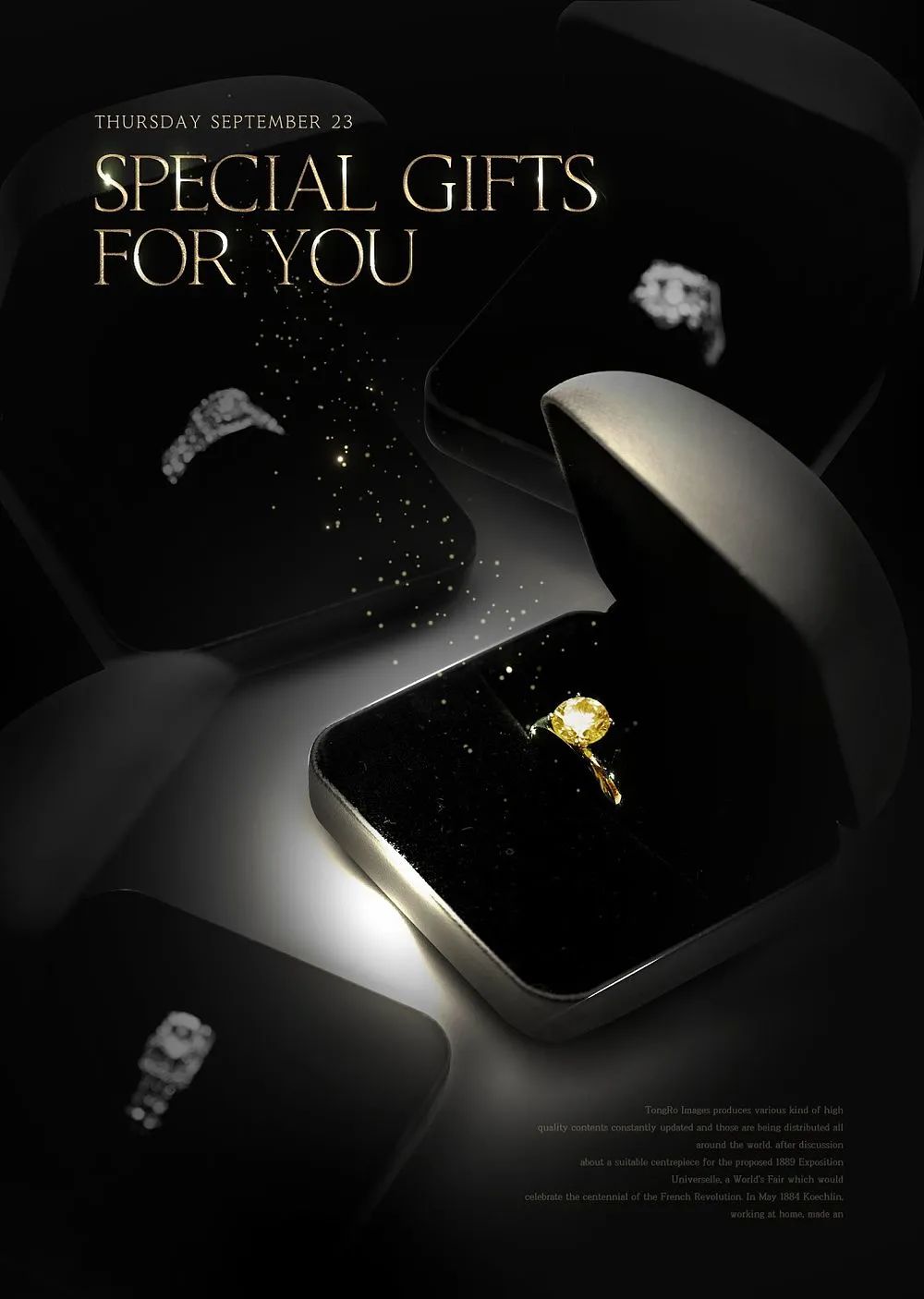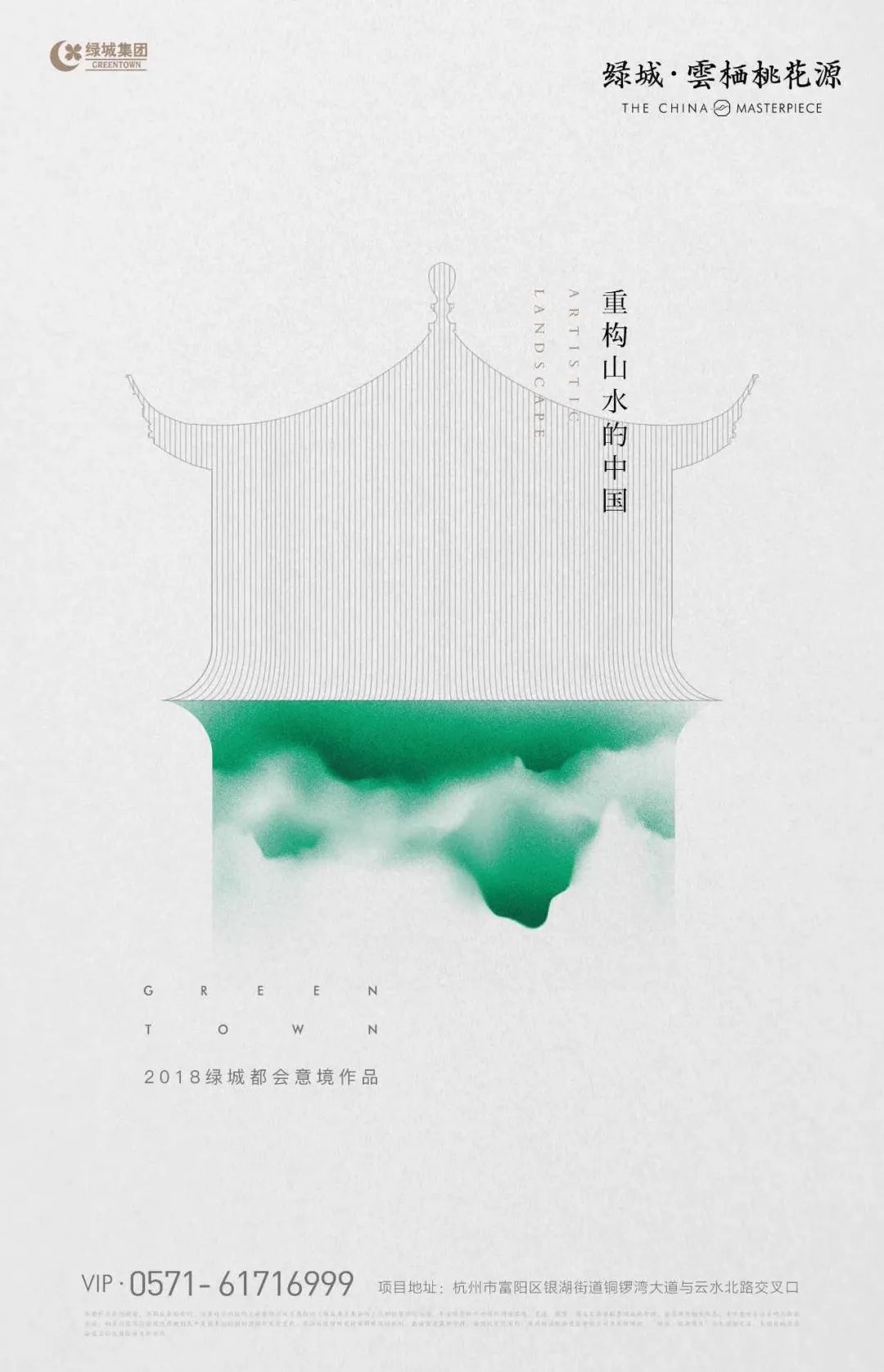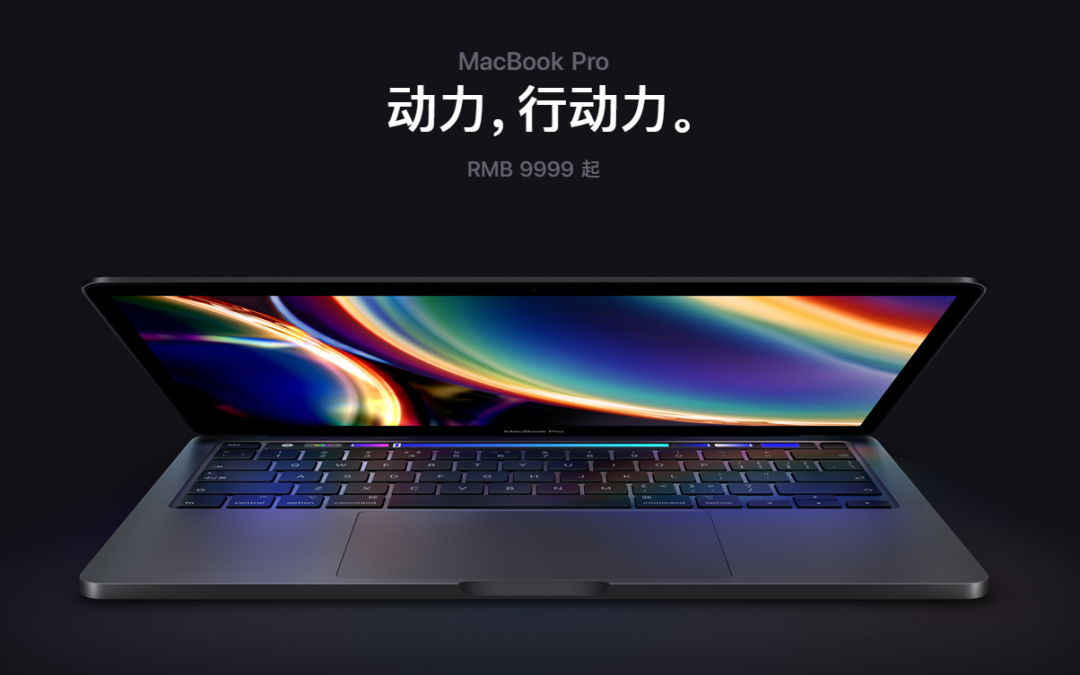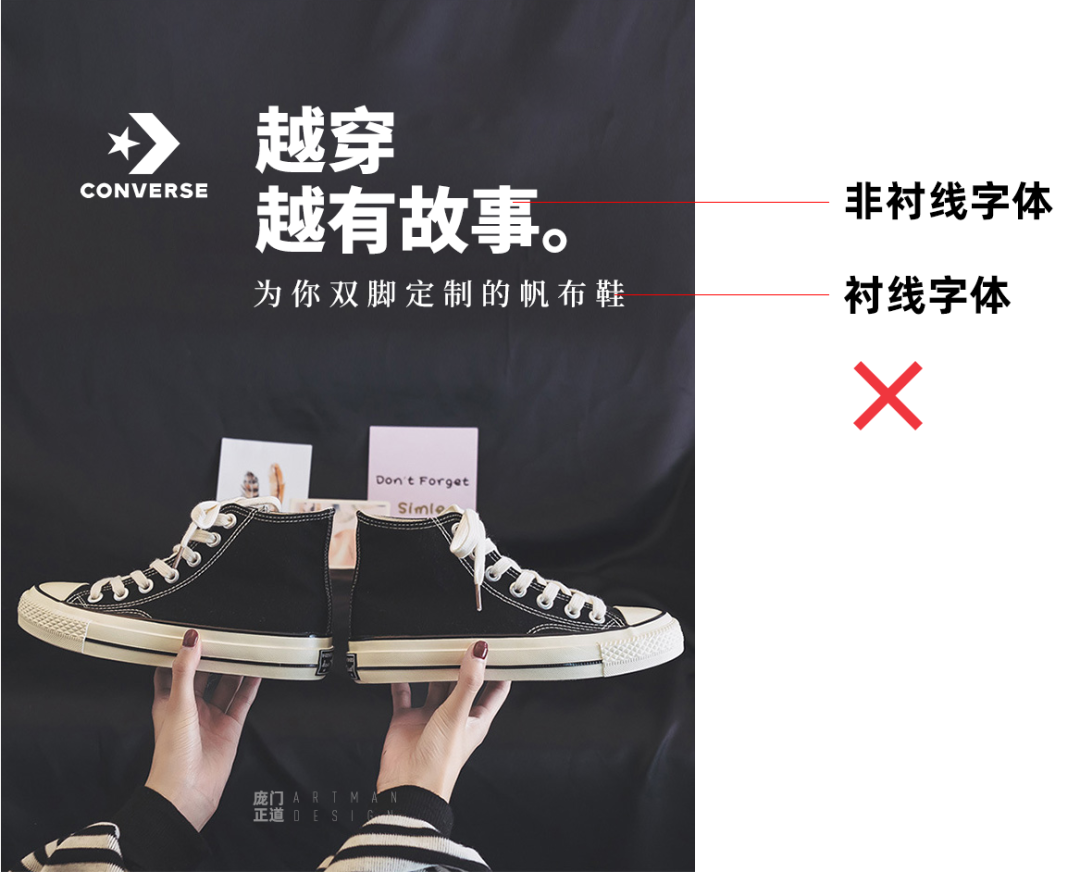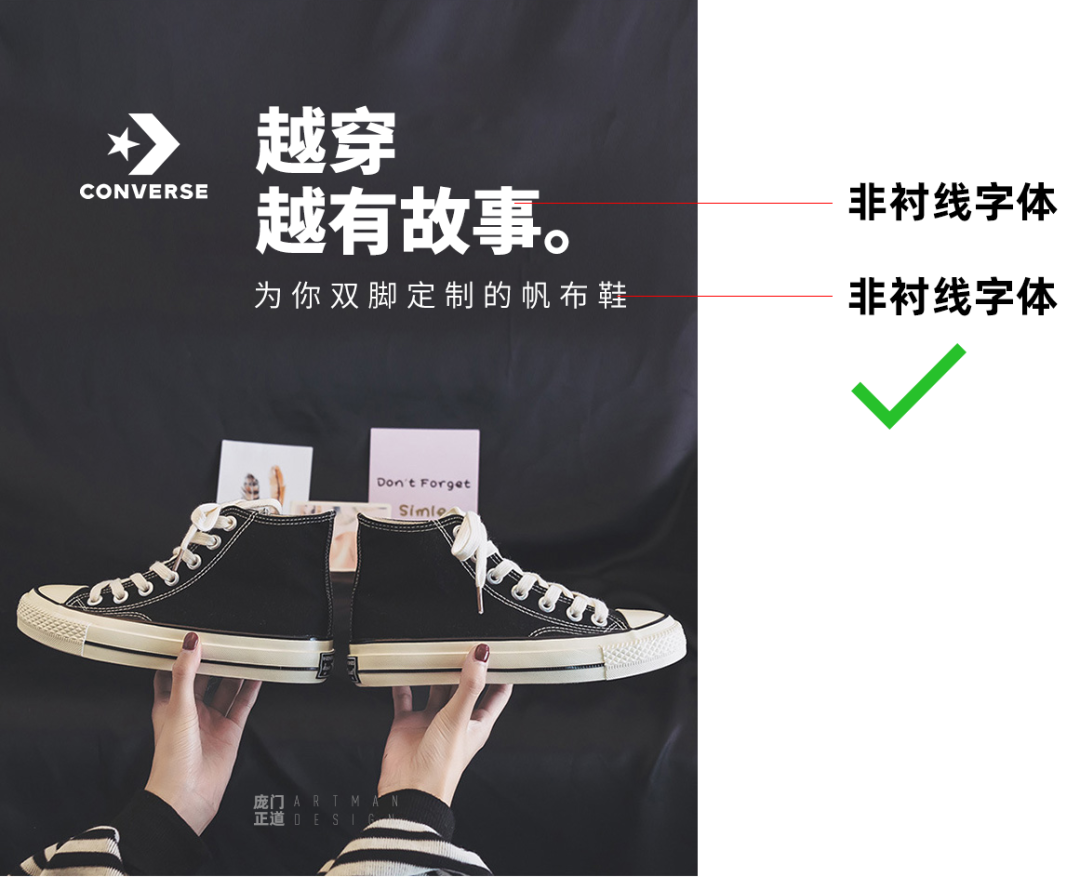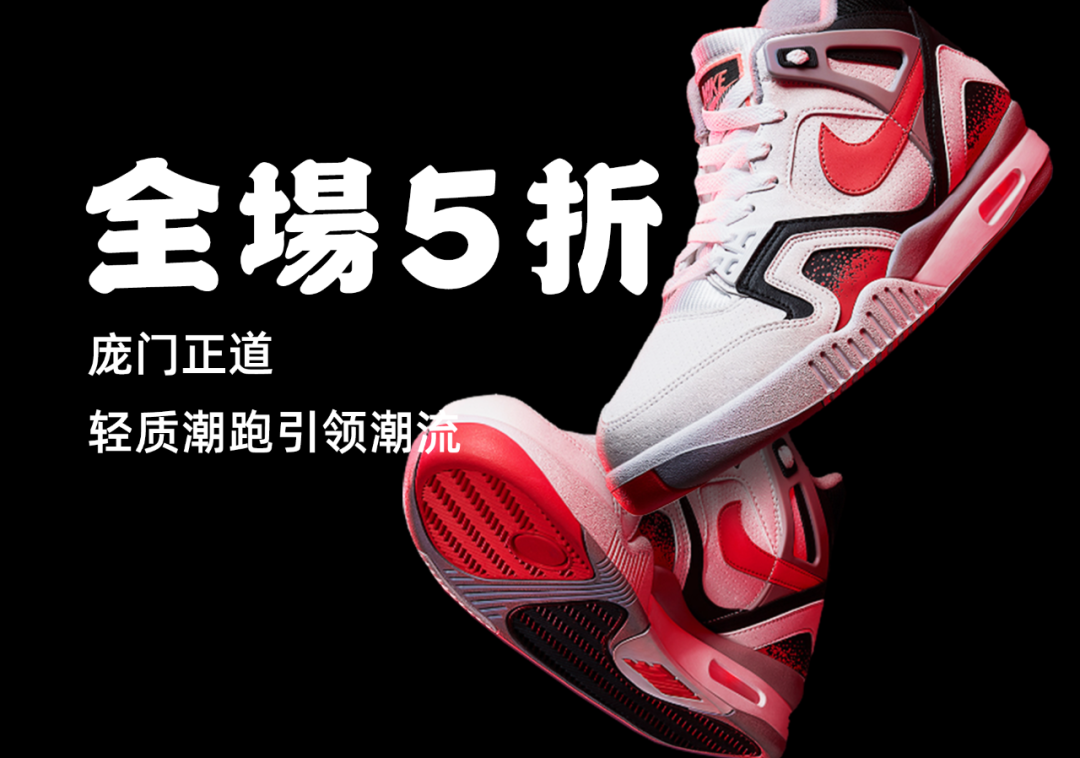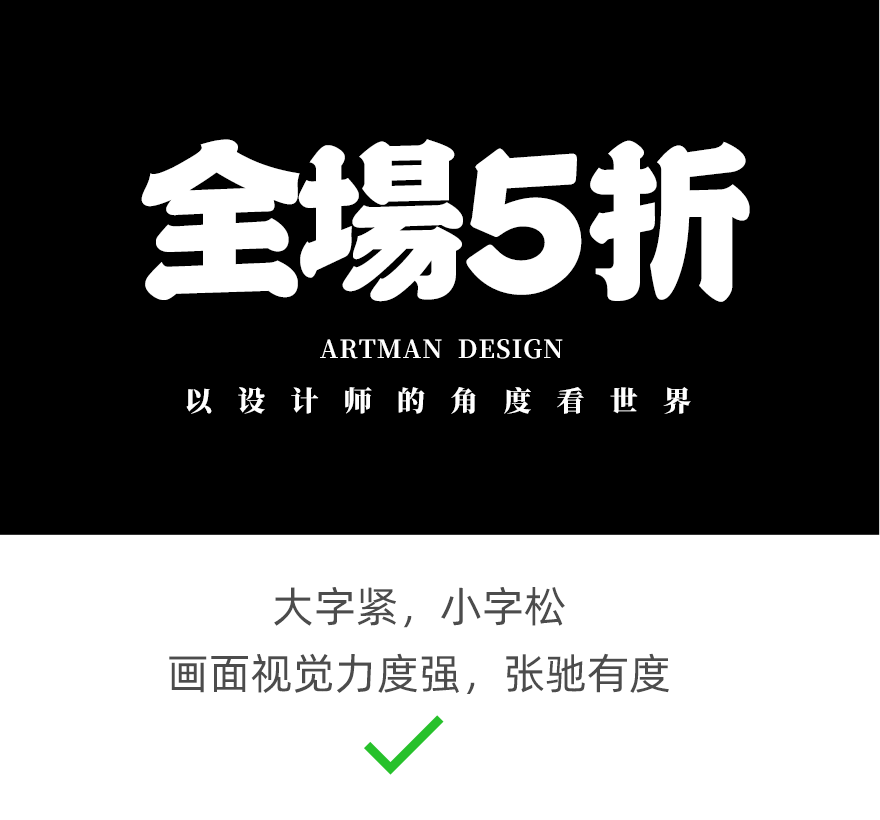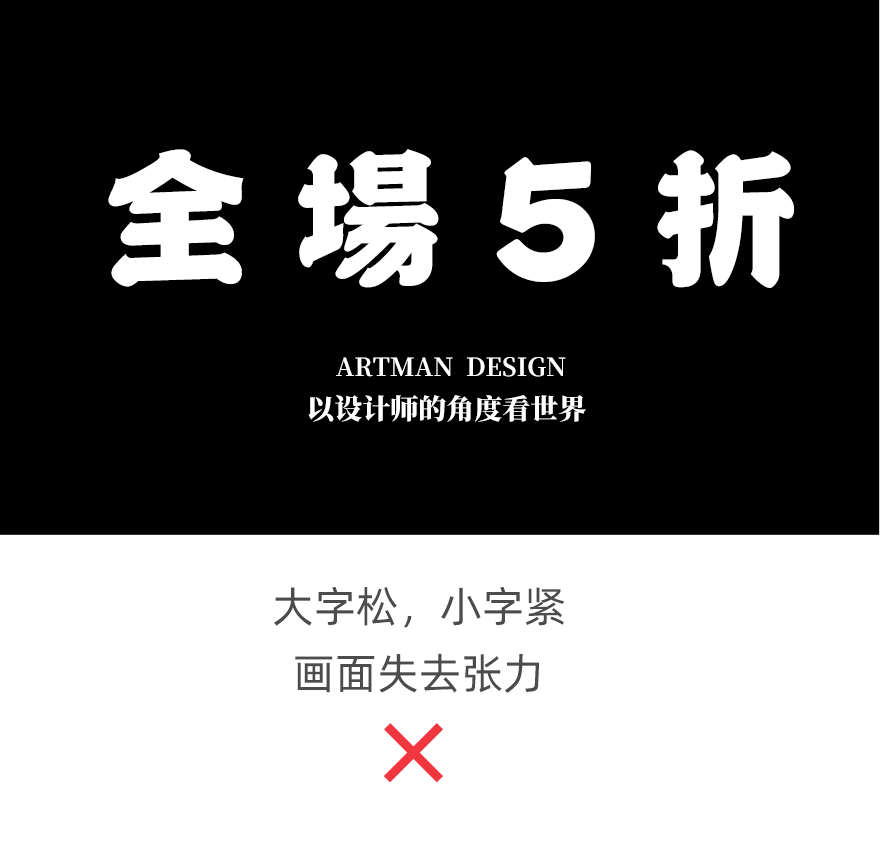
一篇文学会选字体!
我们都知道,平面设计最重要的载体是文字。它可以说是设计的传话筒,设计师通过文字传达信息,同时又将文字作设计的素材,进一步赋予文字更深刻、更丰富的内涵,而字体在这个过程中扮演了重要的角色。
因此,了解字体,学会怎么使用字体,是一个设计师最基本的功底。对于非设计行业的人来说,了解字体的特性,在PPT或者WORD文档中用对字体,也是审美能力的体现。
今天这篇文章,我就带大家从字体的分类,到不同字体适用什么场景,再到排版中的字体使用规则,全方位提升大家对于字体的认识。
选择字体最重要的标准是什么?
两个字:气质。
没错,主要看气质。
先来个案例大家感受一下不同字体的气质区别有多大。
下面这张文艺风的广告图很漂亮对吧?但是字体用得有点粗重呆板,明显和画面的文艺风有点格格不入。
我将字体换成轻盈典雅的宋体后,然后在排版上稍加变化,是不是整个气质就完全不一样了?
所以字体、排版、图片风格这三者是相辅相成的,对排版来说,选对合适的字体,是第一步。
那么问题来了,什么是合适的字体?怎么知道什么画面配什么样字体?
OK,要弄清楚每种字体的性格气质,我们首先需要对所有的字体有个大概的分类。
中文字体:
英文字体:
当然,这只是一个比较大的分类方法,大家只需要有个大概的印象即可。
在实际的应用中,我们对字体有更多的分类维度,为了让大家有一个更直观的印象,我制作了一张四象限图,大家参照这个图,看看相应的字体可以放在哪个位置,这样就对每个字体用在什么场合,就大概心里有谱了。
虽然字体的数量有无数种,但是其实每种字体都可以归到上面的座标图中,大家只要记住这个分类方法,时间久了一眼就能知道某个字体的大概特征,可以怎么用。
说完字体的分类方法,接下来看看在实际的工作中,到底是按什么规则来选择合适的字体。
选字体其实就跟看人一样,第一眼肯定是看到高矮胖瘦啊对不对?所以对字体的气质分类只是内功心法,对字体外观进行分析,然后根据外观来选择它的用处,这才是具体的招式。
接下来我们就按照字体的外观特征,来看看选择字体都有哪些基本的原则。
人分为胖子和瘦子,字体也一样。胖子看起来威猛有力,瘦子瘦弱纤细,这些特征也完全可以对应到字体上来。
粗字体的视觉特征:
从上面这些特征可以看出来,粗字体最大的特征就是力量感、份量感,所以它可以形成强烈的视觉冲击力,一般应用在标题上,而不适合用在需要大段阅读的正文上。
来看看具体的案例。
在跟男性相关的设计上,粗字体绝对是首选。
促销主题,粗字体的份量感可以带来强烈的视觉冲击力!
粗字体带来热闹,视觉冲击力的同时,也会让人有廉价感。尤其是配上让设计师深恶痛绝的红底+金字。
细字体的视觉特征:
和粗字体相对应的,细字体容易让人联想到瘦弱的女性,没有粗字的冲击力,但是更加精致典雅,在一些高端品牌的设计中常常可以看到细字体的应用。
来看看具体的案例。
女性主题的设计:
在一些高端的设计中,细字体可以让画面显得精致优雅:
看到细细小小的字体,是不是有种买不起的感觉?
衬线和非衬线的说法其实是来源于英文,但是在汉字上也适用。
英文:
汉字:
两者最大的区别就是衬线字体的笔划上会多一些装饰细节,而非衬线字体的笔划则更简洁清晰。
衬线字体的视觉特征:
衬线字体的装饰细节其实是来自手写字特点的保留,所以它在细节上更加精致,更加富有传统书法的美感。因此在一些人文类的设计,或者追求精致感的设计中,经常可以看到衬线字体的应用。
来看看具体应用案例。
历史人文类的设计,一般都选择衬线字体:
很多高端品牌都喜欢用衬线字体,以表达出精致典雅的氛围:
要文艺小清新?那肯定少不了衬线体。
非衬线字体的视觉特征:
非衬线字体发源于现代,它的出现纯粹是出于功能性的考虑。非衬线字体去除了字体上有关传统书法的所有特点,让字本身变得更中庸,没有特点。但同时也具有更简洁易读,以及更有包容性。
来看看具体的应用案例。
跟现代有关的主题,选择非衬线字体:
年轻、青春的主题,也适合非衬线字体:
这里说的常规体是指我们常用的黑体宋体,工整、可辨识性高。需要长时间阅读的段落文字一般使用常规字体。
常规字体的视觉特征:
正式、严肃的主题,一般选择常规、工整的字体。
手写字体的视觉特征:
相对比常规字体,手写体更加活泼、个性,风格性极强,可以营造强烈的视觉冲击力。缺点是可辨识性比较差,当文字数量较多时,会影响阅读效率。所以一般只用在简短的标题上,不可使用于正文。
生活化的主题,可以使用手写体来表达态度。
低龄化的主题,用手写体来体现活泼的一面。
在排版中,适当加入手写字体,可以让画面充满活力。
在一些促销页面中,可以使用手写字体来放大视觉冲击力。
弄清楚每种字体怎么用之后,接下来我们看看在排版中,又有哪些关于字体使用的基本原则。
字体和排版两者的关系是密不可分的,尽管现在市面上的字体数量有无限多,而且你可以将它们无限组合。但如果你不遵守一些最基本的字体使用规则,那么你的字体肯定是用多错多。
OK,下面我们来看看有哪些字体使用基本原则是我们必须遵守的。
一、字体数量
字体使用的首要原则就是要克制。请新手设计师一定记住,在同一个页面中,字体的数量尽量控制在3种以内。
最常用的字体使用方案是2种字体:标题 + 副标题(正文)
如果画面中有很重要的信息需要标示出来,可以考虑加入一种特殊字体,这样就变成了3种字体:标题+副标题(正文) + 重点信息
基本上,上面两种字体使用方案可以覆盖了绝大部分需求,如果你没有十足的把握,尽量使用这两套方案。如果你确实想增加新的字体,请务必想清楚是不是有足够的理由。
二、可阅读性
字体最本质的功能是信息的载体,所以可阅读性是字体的首要功能。不同的字体它的可阅读性差异是非常大的,如果我们的画面中有大段文字,这个 时候你就需要特别注意字体的辨别性问题。
对于字体的可阅读性,大家记住下面3条原则即可:
1、常规字体比手写、变形字体可读性更好。
2、字面宽,看起来胖胖的字体,比瘦高型的字体更好阅读。
3、非衬线字体比衬线字体可读性更好。
三、字体组合
前面我们说过,不同的字体所呈现出来的气质特征会很不一样。那么我们将不同的字体放在同一个画面,就必须考虑它们的风格是否匹配的问题。
在大数情况下,页面上的所有字体都应该采用同样性质的字体,这样可以产生一种协调的关系。
1、衬线与非衬线字体的组合。
如果主标题采用的是衬线字体,那么副标题和正文也尽量采用衬线字体。
如果主标题用了黑体,而副标题用了宋体,两者在气质上不搭。
不只汉字与汉字的组合,汉字与英文的组合也要符合这样的规律。
当然,在设计中肯定没有绝对的事情。
比如手写字标题的组合,就跟衬线与非衬线字组合的规则不一样。
2、手写体与常规字体的组合。
一般来说,我们可以在主标题上使用手写体,而在副标题上使用常规的黑体、宋体等,这样既让整体排版保持视觉张力,又让整个版式不至于失去重心平衡。
前面我们说过,手写字体的优点是有视觉冲击力,缺点则是散乱,不工整,不好阅读,因此手写字切不可以滥用。
如果主标题使用了手写字,副标题再使用手写字的话,层次感上就没那么清晰,更重要的,副标题的可阅读性也大大减弱了。
3、大字与小字的组合。
关于大字和小字,宋朝大书法家苏东坡有个说法是“大字难于结密而无间,小字难于宽绰而有余。”
啥意思呢?就是说大字要写得紧凑,而小字要写得宽松。虽然这是书法理论,但是用于文字排版也一样成立。
我们来看个小例子。
一般用大标题都是为了强化视觉冲击力,紧凑的大标题可以让画面信息更聚焦,更容易抓住用户眼球。而松散的小字,则可以很好的平衡画面,让整个画面显得张驰有度。
再来对比一下相反的效果:
反之我们可以看到,大字散开,小字聚拢会让画面没有重点,视觉上过于松散没有重点,画面失去张力。
大字和小字的组合是几乎所有设计中都会遇到,下面我们以鞋子为主题,做一张广告banner,看看大字和小字的组合在设计中的应用。
第一步,抠好素材图,并且摆放好位置。在这一步就需要大概想好整个画面的构图,我这里是打算做左右构图,所以将产品放在右边。
第二步,将文案打上去。
第三步,按照前面我们讲的大小和小字的组合方式,将大字收紧,增大面积,小字加大间距,这样整个文案的整体既拉开了对比,又松驰有度。
第四步,在背景上增加红色分割,增加画面的对比度。
第五步,最后增加一些细节,提升版式的活力。